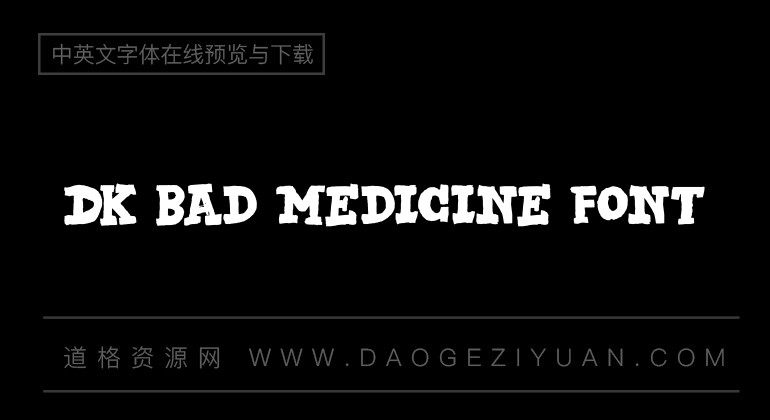
DK Bad Medicine Font
DK Bad Medicine Font是一种非常独特的字体风格,它的设计灵感来自于老式的纹身艺术。这种字体的特点是有很多的笔画和细节,使它看起来非常有力量和狂野。它的字母形状也非常不规则,给人一种手绘的感觉。 DK Bad Medicine Font适用于许多不同的项目,特别是那些需要一个具有强烈视觉冲击力的设计。它可以用于标志、海报、纹身艺术、音乐封面、T恤设计等等。 这种字体可以在许多不同的软件中使用,包括Adobe Photoshop、Illustrator、InDesign等等。它也可以在许多不同的文件格式中使用,包括OTF、TTF、WOFF等等。
DK Bad Medicine Font是一款非常不错的手写艺术字体,具有很好的视觉感,适合于文化类的宣传设计、商业类品牌的广告和产品包装设计以及个性化文字排版等较多场景。